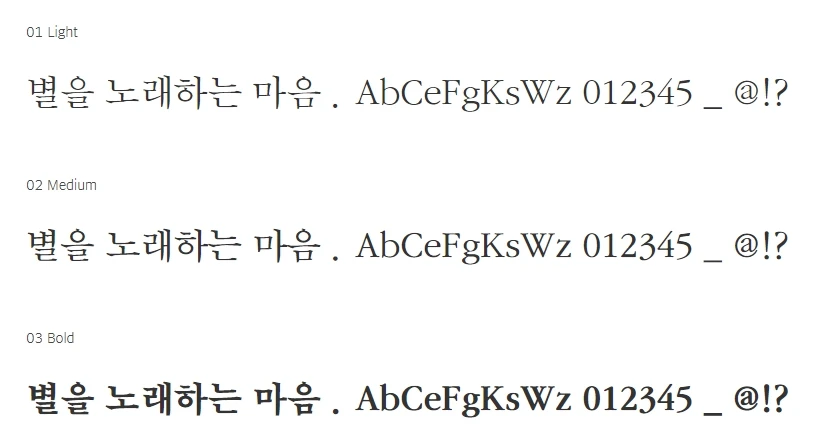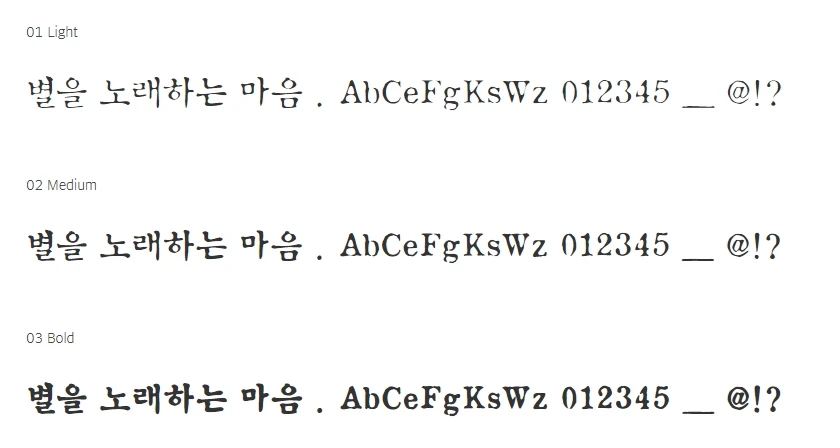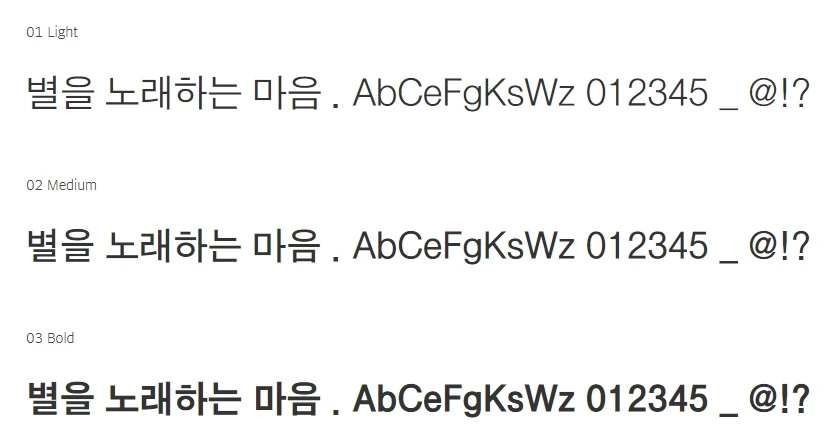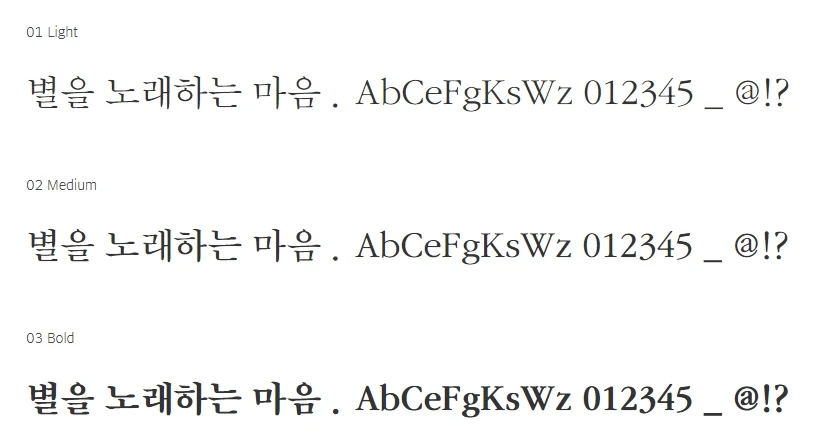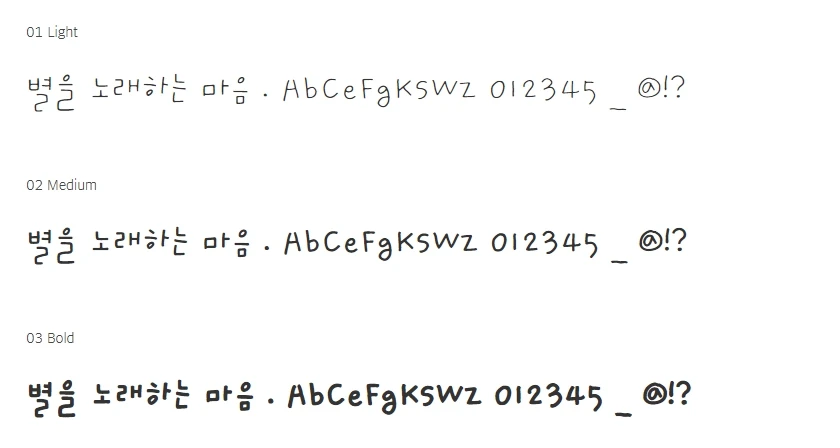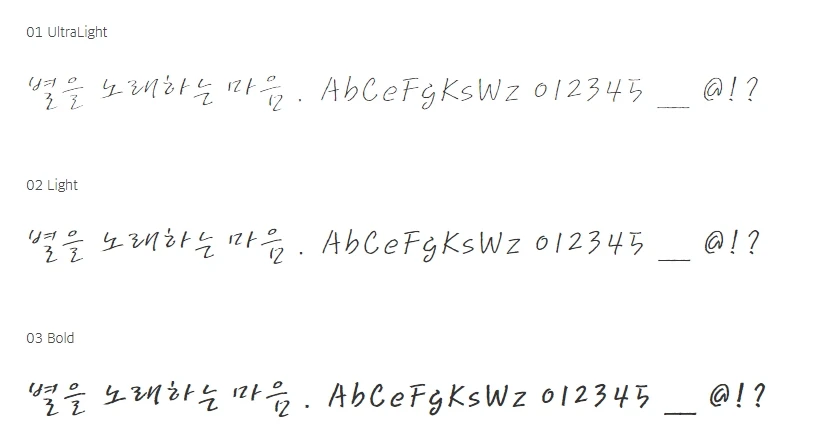
산돌은 1984년 설립된 한국 최초의 폰트 회사입니다. 지난 30여년 동안 산돌에서 개발해 온 600여개의 글꼴 중 1990년대에 출시되어 지금까지 꾸준히 사랑받고 있는 폰트를 소개합니다.
산돌고딕
1995년 출시. 산돌고딕은 기본 중의 기본 폰트로 본문에 가장 적합하게 디자인된 산돌의 스테디셀러이다.
산돌명조
1995년 출시. 산돌명조는 완벽한 균형이 주는 뛰어난 가독성으로 산돌 본문체의 가장 기본이 되는 폰트이다.
산돌광수
2000년 출시. 산돌광수는 인기웹툰 "광수생각"의 저자 박광수의 손글씨를 폰트로 만든 것이다.
산돌비상
1998년 출시. 산돌비상은 기존의 틀을 벗어난 가볍고 자유로운 감수성의 손글씨 폰트이다.
산돌성경
1998년 출시. 산돌성경은 한글판 성경전서를 복원하여 클래식한 느낌을 잘 살린 폰트이다.
산돌제비
1992년 출시. 산돌제비는 명조체를 현대적으로 재해석한 산돌의 대표적인 본문용 폰트이다.